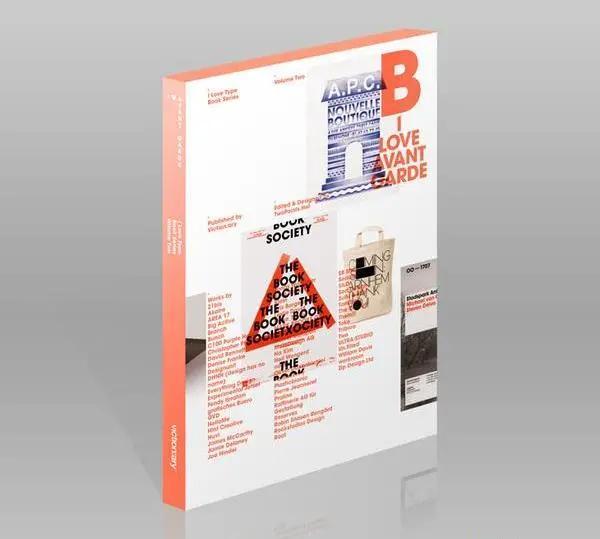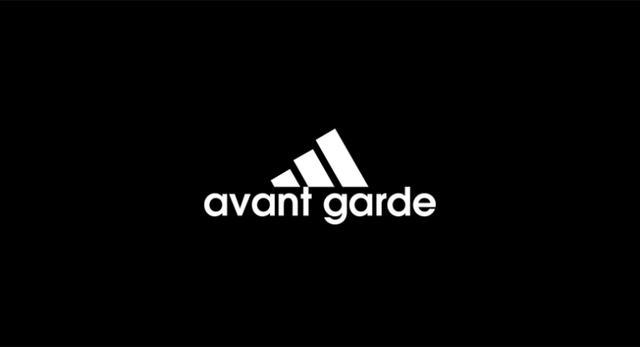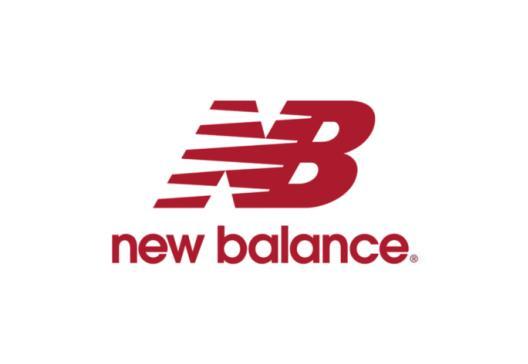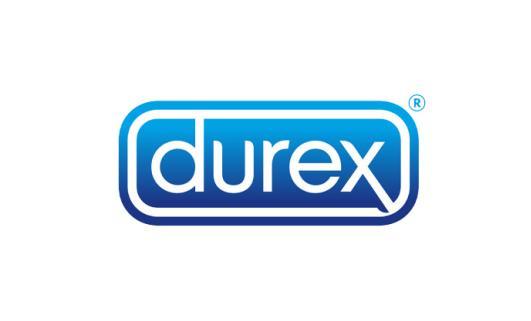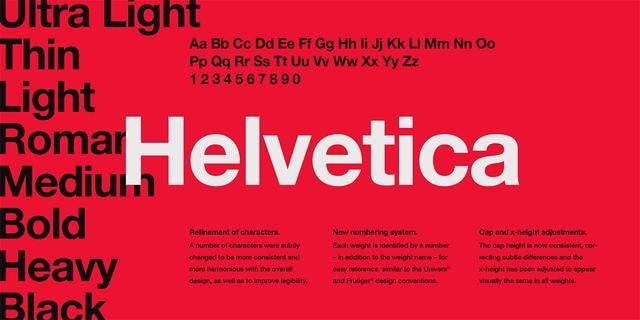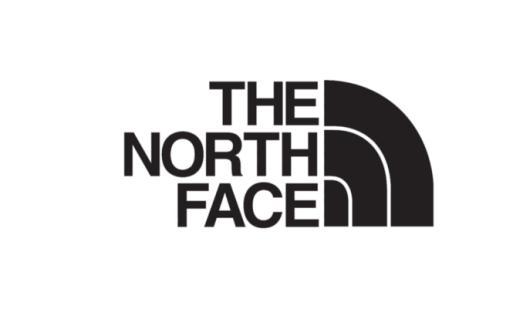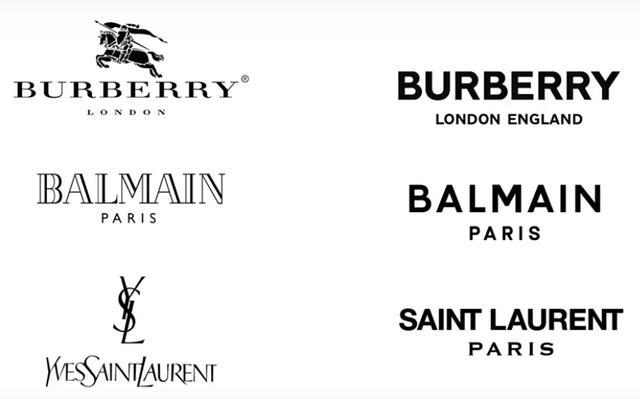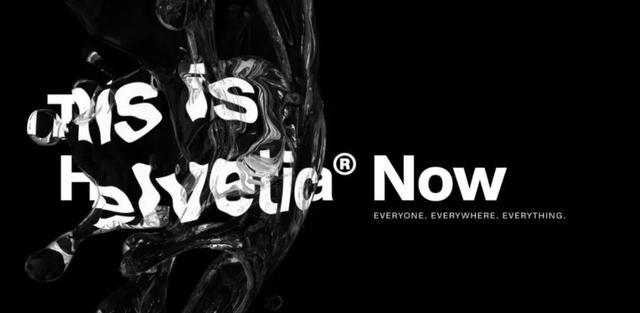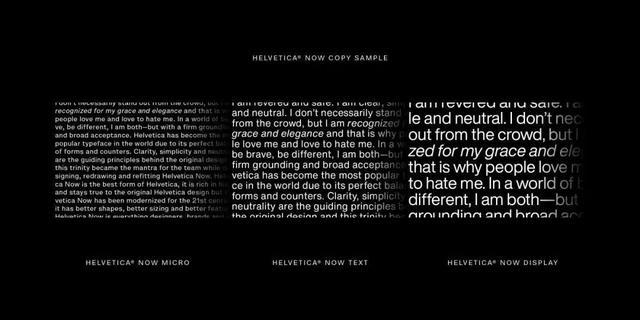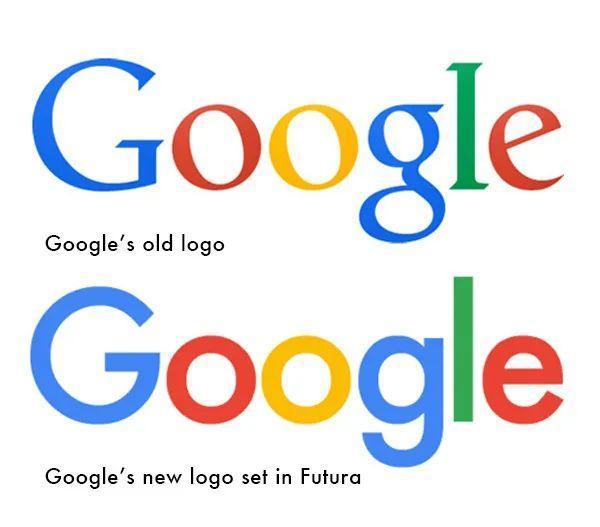
原来这些大牌logo用的是这些字体
文字 LOGO 的设计经常会采用优质的经典字体作为基底,虽然很多品牌LOGO 在设计的时候,会专门设计字体,但是实际上,很多品牌的 LOGO 其实是使用既有的字体来进行小幅度优化再进行设计的。即使是那些你感觉很熟悉的字体,同样可以借助一些并不复杂的方式,来制造出爆款设计,营造出令人过目不忘的独特视觉体验。
01
Avant Garde
Avant Garde 字体原本是 Avant Garde 杂志的 LOGO 字体,由 Herb Lubalin 创建。之后他与卢巴林设计公司的合伙人 Tom Carnase 一同努力,将这款字体完善成为一套完整的标准字体。由于 Avant Garde 出色的几何特征,很多品牌 LOGO 在设计的时候都考虑并采用了这款字体。
02
Helvetica
Helvetica是一种经典的现代非衬线字体,于1957年由瑞士字体设计师爱德华德·霍夫曼 (Eduard Hoffmann) 和马克斯·米耶丁格 (Max Miedinger) 设计,体现了瑞士设计的理性主义精神,同时被认为是现代主义设计理念的典范。很多品牌都使用 Helvetica 字体来作为设计的基底,借助基础的倾斜、色彩和装饰,来营造独特品牌视觉特征和气质。
吉普汽车和雀巢咖啡这两个品牌的标志设计都以使用了世界上最受欢迎的字体Helvitica而闻名。
“无论你朝向哪里,你总是能看到各种字体。但其中有一种可能是最多见的,那就是Helvetica。它们的存在彷佛原本就是环境中的一部分。”国际平面设计协会Massimo Vignello主席给予Helvetica字体这样高的评价。
在过去的几年中,许多奢侈品在升级品牌形象时也开始采用Helvetica字体或者与其外形相似的无衬线字体作为logo标志字体。
即便Helvetica如今这么受欢迎,作为一款上世纪的字体,在数字化和手机终端崛起的时代,它也需要适应和更新。拥有 Helvetica 字体版权的 Monoytpe 在 2019 年推出了 Helvetica Now 字体,特别为任何屏幕放大或缩小而设计,由数十名设计师和工程师耗费5年时间研究和协作。
03
Futura
Futura 字体的灵感来自包豪斯运动,继承了包豪斯的设计理念,由设计师保罗伦纳1924年至1926年所创建。Futura 不仅本身大获成功,而且成功催生了新的几何无衬线字体。
在国外的设计圈中,设计师私下经常调侃,在设计的时候尝试过很多不同的字体,最后总会用回 Futura。
04
Avenir
Avenir 是由 Adrian Frutiger 设计的一款无衬线字体,最初于1988年由莱诺字体公司发布。Avenir 在法语当中是 “未来” 的意思,在某种意义上,它和 Futura 在精神内核上有所呼应。和 Helvetica 一样,Avenir 字体是为了 “基本适合用在任何平面设计场合” 的一种字体。
Avenir 这款字体整体呈现出一种中性、去性格化的特点,是一种气质 “透明” 的字体。
05
Gotham
Gotham 是一款 2000 年的时候为 GQ 所设计,并于 2002 年向公众开放的字体。它出现的地方很多,从可乐瓶、推特、Spotify、Netflix、Saks 到纽约大学、翠贝卡电影节,这还不止,包括《柯南秀》和《周六夜现场》在内的电视剧、包括《盗梦空间》、《点球成金》、《可爱的骨头》和《月光男孩》在内的电影,都用到了这一字体。
Gotham 原本的设计构思中,是要呈现出一种 “新鲜和阳刚” 的气息,不过真正投入使用的时候,才发现它的细体非常的具有女性的优雅感。Gotham 在现代的品牌和 LOGO 设计中应用广泛,它兼顾了灵活和高级感。
06
Univers
Univers 字体和 Avenir 同样出自设计师 Adrian Frutiger 之手,不过 Univers 是 Frutiger 的早期字体作品,它和 Helvetica 并称为 “瑞士风格字体” ,最初是作为一款照相排印字体所发布的。
Univers 字体的字重控制和其他的字体不同,是按照数字来进行区分的,到现在 Univers 字体族当中所包含的变体已经非常之多了,多达44种,不同宽度、粗细变化的衍生字体使得它作为 LOGO 字体非常方便。
07
Myriad
Myriad 字体就是 Adobe 的LOGO 品牌用字,这款字体原本就是 Robert Slimbach 和 Carol Twombly 为 Adobe 定制的字体。Myriad 字体的基底是 Frutiger 字体 —— 而 Frutiger 、Univers、Avenir 三款字体系出同门,都出自 Adrian Frutiger 之手。
和很多早期的非衬线体字体不同,Myriad 从一开始就是为了数字化而设计的,字体家族内不同字重、样式的变化是动态的,通过不同的字母宽度调解平衡,给人温暖友好的感觉,而这一点也使得它在屏幕和印刷品上,显得更加协调和自然。
08
Arial
Arial 这款字体能走向世界,和微软息息相关。这款 Monotype 出品的数字字体是随着当年的 Windows 3.1 操作系统和当时最新的 Truetype 技术一同分发出来的,它的竞争对象则是最为经典的 Helvetica 字体,在视觉上,Arial 和 Helvetica 是非常相近的。
Monatype 在设计Arial 时,考虑到会在电脑上面使用,在字体及字距上都作了一些细微的调整和变动,以增加它在电脑屏幕上不同分辨率下的可读性。